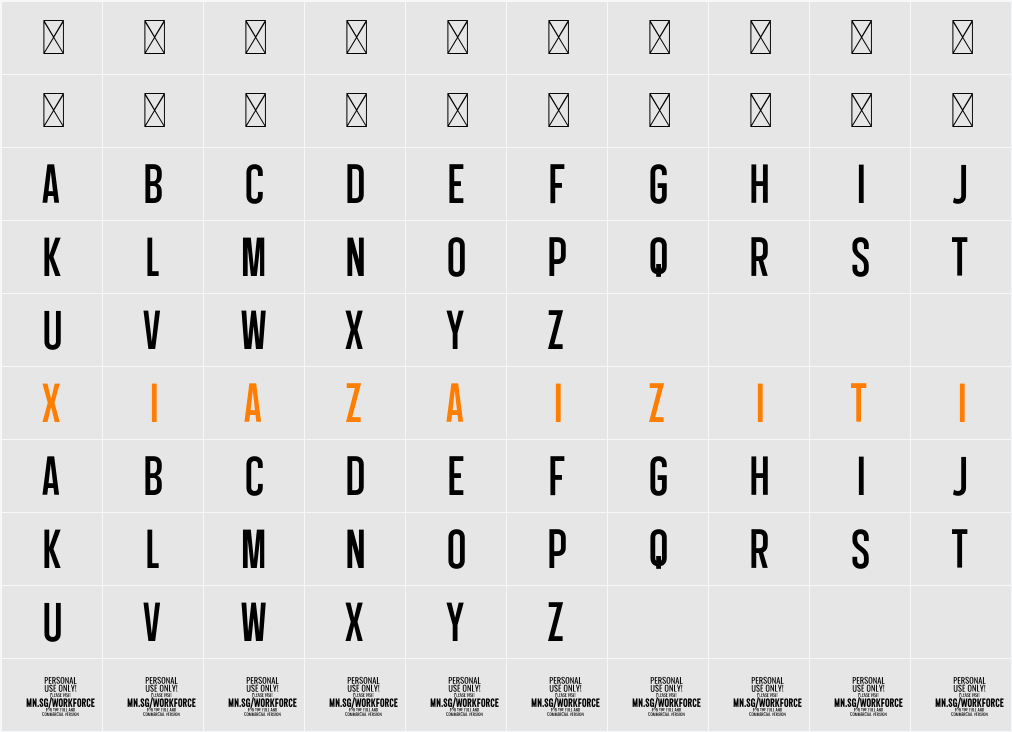
Workforce Sans PERSONAL USE
Workforce Sans PERSONAL USE,这款字体结构工整、笔画清晰,兼顾美观与易读性,适用于标题、正文、海报、包装、LOGO 等多种场景。字形优雅稳定,风格百搭耐看,适配日常排版与创意设计,让文字呈现更舒适、更具质感。Workforce Sans PERSONAL USE一笔一画,皆是细节,以均衡的比例、流畅的线条打造舒适视觉体验,字形端正大气,风格简约现代。无论是商业设计、品牌宣传还是日常排版,都能轻松驾驭,让文字更有格调与力量。Workforce Sans PERSONAL USE字体下载。